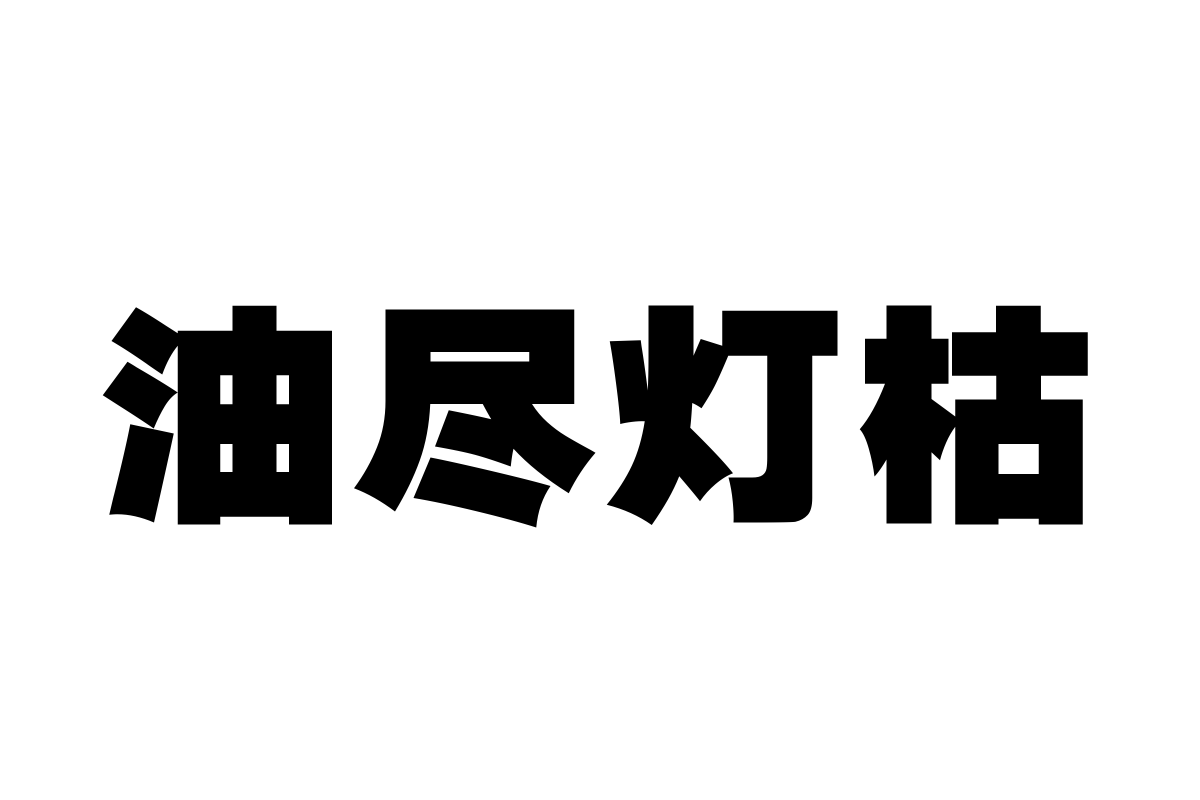
三极超粗极黑简体字体是一种非常独特的字体,它采用了三极超粗的设计和极黑的颜色。这种字体的笔画粗细不一,给人一种强烈的视觉冲击力。同时,它的极黑颜色也使得整个字体显得更加醒目和突出。
这种字体的特点是笔画粗细不一,线条流畅,给人一种强烈的视觉冲击力。同时,它的极黑颜色也使得整个字体显得更加醒目和突出。这种字体适合用于需要强烈视觉效果的场合,如广告、海报等。